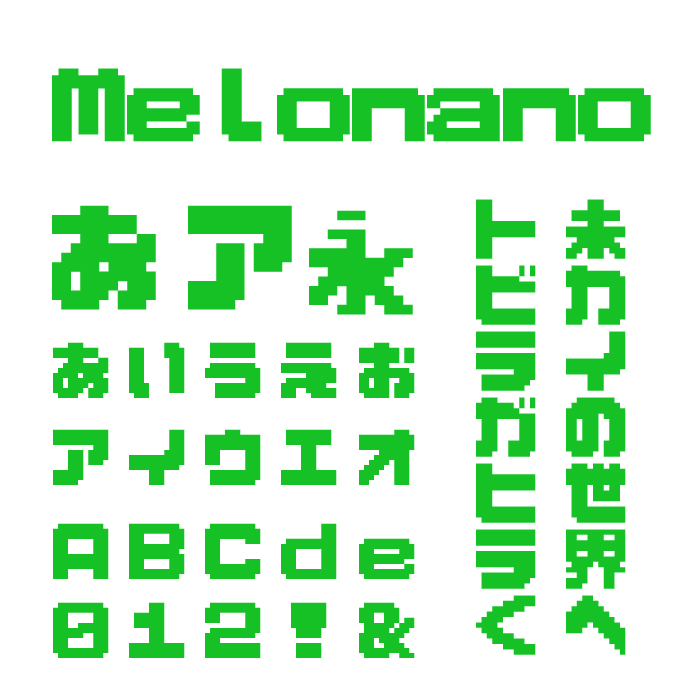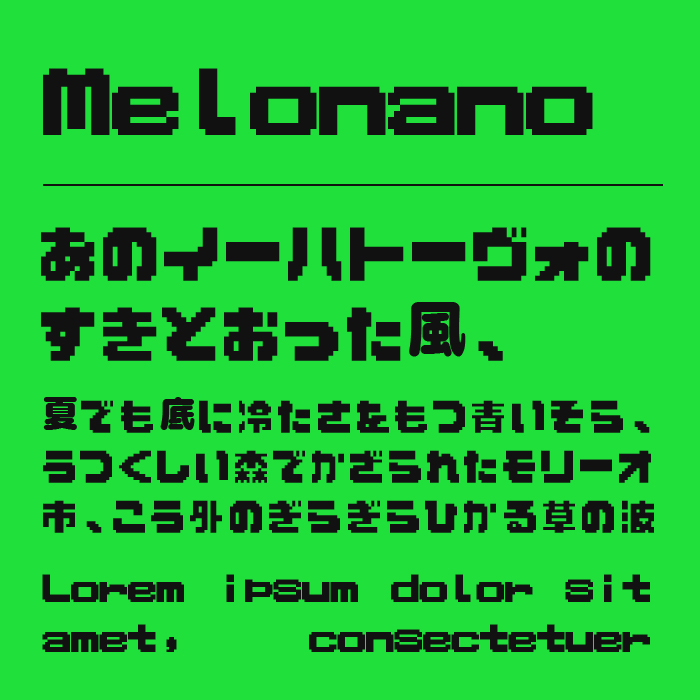
Melonanoフォントは、太めなドットを意識したようなブロック感のあるピクセル風デザインが特徴のフォントです。
ゲームやレトロなデジタル表現との親和性が高く、画面上での見栄えが抜群。太めなドットがチャームポイントで、カクカクしたフォルムがリズム感を生み出す雰囲気がとても良いです。
すべての文字が統一されたルールに基づいて設計されており、視認性とデザイン性を両立。ビットマップ系やレトロゲーム風の演出、アーケード感を出したいビジュアルにうってつけのフォントです。
収録文字は、漢字・ひらがな・カタカナ・アルファベット・数字・記号が収録。